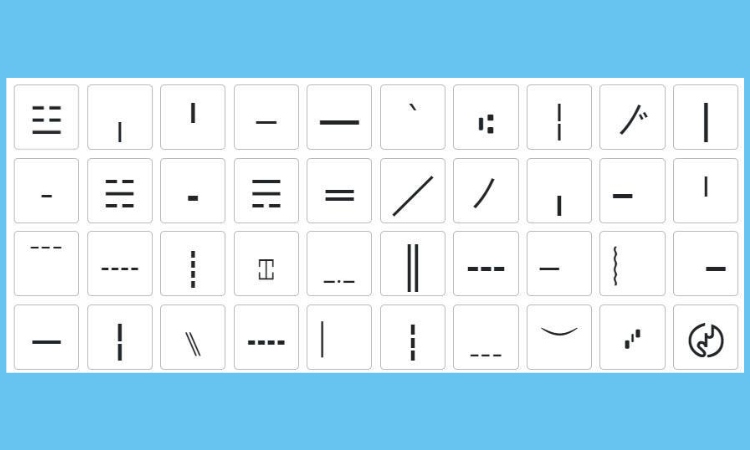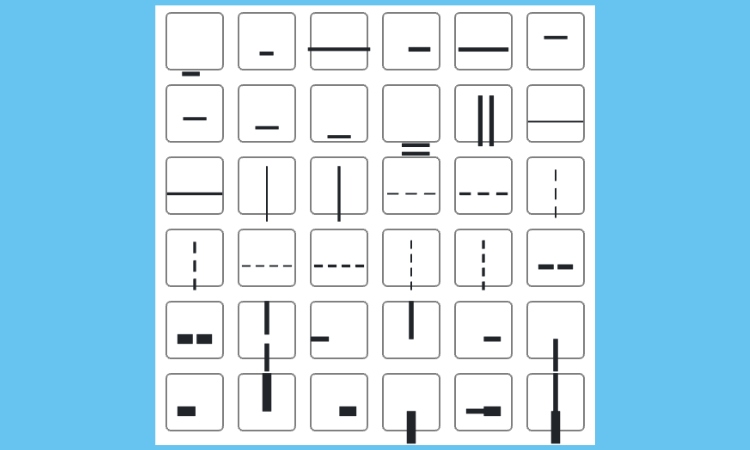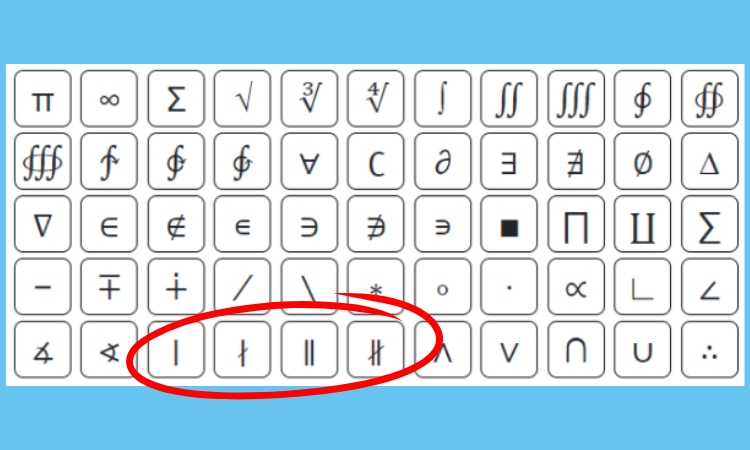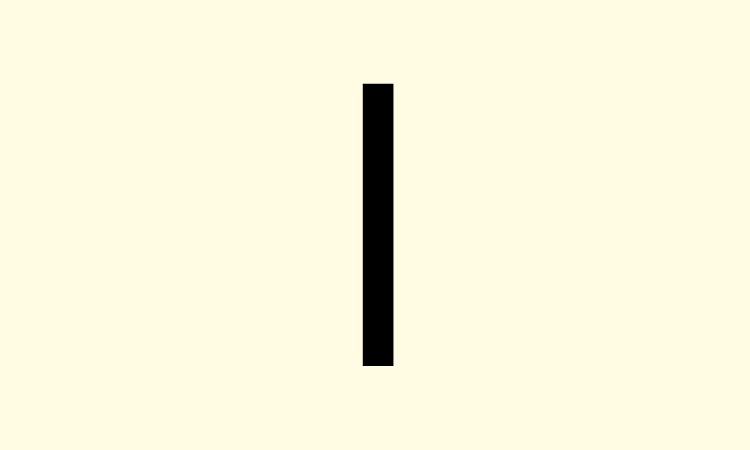
75 kí tự dấu gạch dọc siêu đẹp giúp tên hiển thị nổi bật
Dấu gạch dọc là một kí tự phổ biến dùng để phân tách nội dung, tạo điểm nhấn trong tên hiển thị, bio mạng xã hội hoặc văn bản. Bộ sưu tập dưới đây sẽ giúp bạn dễ dàng sao chép các kí tự đặc biệt gạch dọc, kết hợp với icon để tạo nên những cái tên thật ấn tượng.
Dấu gạch dọc là một dạng kí tự hình thẳng đứng, thường được dùng trong lập trình, định dạng văn bản hoặc để phân cách các phần thông tin. Trong thiết kế tên nhân vật, bio mạng xã hội hay status, gạch dọc mang đến cảm giác hiện đại, sắc sảo và chuyên nghiệp. Nhiều người dùng còn sử dụng các dạng kí tự dấu gạch để tạo hiệu ứng “đường kẻ” thẳng đứng giúp tên hiển thị trở nên ấn tượng hơn.
Danh sách dưới đây gồm toàn bộ các kí tự dấu gạch dọc, gạch dọc dạng mảnh, dạng dày, nét đứt, cột đôi,... được sử dụng nhiều nhất hiện nay.
Đây là những kiểu kí tự phổ biến, dễ sử dụng và đảm bảo tương thích tốt với hầu hết các nền tảng, phù hợp khi bạn cần tạo điểm nhấn đơn giản hoặc phân tách nội dung một cách gọn gàng:
Phần lớn những ký tự này thường được sử dụng trong các ngôn ngữ lập trình hoặc trong việc biểu diễn dữ liệu theo dạng bảng biểu, cấu trúc logic.
Bạn có thể sử dụng những kí tự độc đáo sau để tạo điểm nhấn sáng tạo cho tên nhân vật trong game, phần giới thiệu trên TikTok hoặc caption Instagram thật nổi bật và cuốn hút:
Trong khi dấu gạch dọc mang phong cách chia cột hoặc ngắt dòng, thì kí tự đặc biệt gạch ngang lại tạo hiệu ứng phân tách ngang. Còn dấu 3 chấm dọc thường được dùng như biểu tượng “menu mở rộng” trong giao diện người dùng.
Thường dùng để tạo hiệu ứng đường phân cách:
Dạng biểu tượng thường gặp trên giao diện điện thoại, menu tùy chọn:
Sự kết hợp giữa các loại kí tự đặc biệt gạch ngang, dấu 3 chấm dọc và dấu gạch dọc mang đến nhiều lựa chọn sáng tạo trong thiết kế tên và nội dung.
Dưới đây là một vài ví dụ đặt tên ngầu và đẹp mắt:
Bạn có thể dùng trực tiếp hoặc kết hợp các kí tự đặc biệt gạch ngang và gạch chéo để tăng sự sáng tạo cho tên mình.
Bạn có thể tham khảo các mẫu dưới đây để đặt tên game, làm bio mạng xã hội hoặc tạo hiệu ứng văn bản với dấu gạch dọc, kết hợp nhiều phong cách đa dạng từ dễ thương đến cá tính.
Dưới đây là những mẫu kiểu chữ đẹp được tạo bằng kí tự đặc biệt, mang phong cách nhẹ nhàng, cá tính hoặc nghệ thuật, lý tưởng để trang trí tên hiển thị:
Những mẫu kí tự ngẫu nhiên dưới đây được thiết kế sáng tạo, thường dùng để tạo điểm nhấn hoặc dùng trong các kiểu nickname độc đáo:
Danh sách sau là các mẫu tên sử dụng kí tự xáo trộn cực kỳ bắt mắt, phù hợp để làm tên game hoặc mô tả cá tính mạnh:
Đây là bộ sưu tập lớn nhất gồm các kiểu kí tự chữ gạch dọc kết hợp với nhiều phong cách từ Gothic, in nghiêng, Hàn - Nhật - Trung đến kiểu Latin hiện đại:
Rất phù hợp. Trong văn bản, bảng biểu hoặc khi viết caption mô tả, dấu gạch dọc giúp phân tách rõ ràng từng phần thông tin, thay thế cho dấu chấm phẩy hoặc dấu gạch ngang truyền thống. Ví dụ: Tên | Tuổi | Nghề nghiệp.